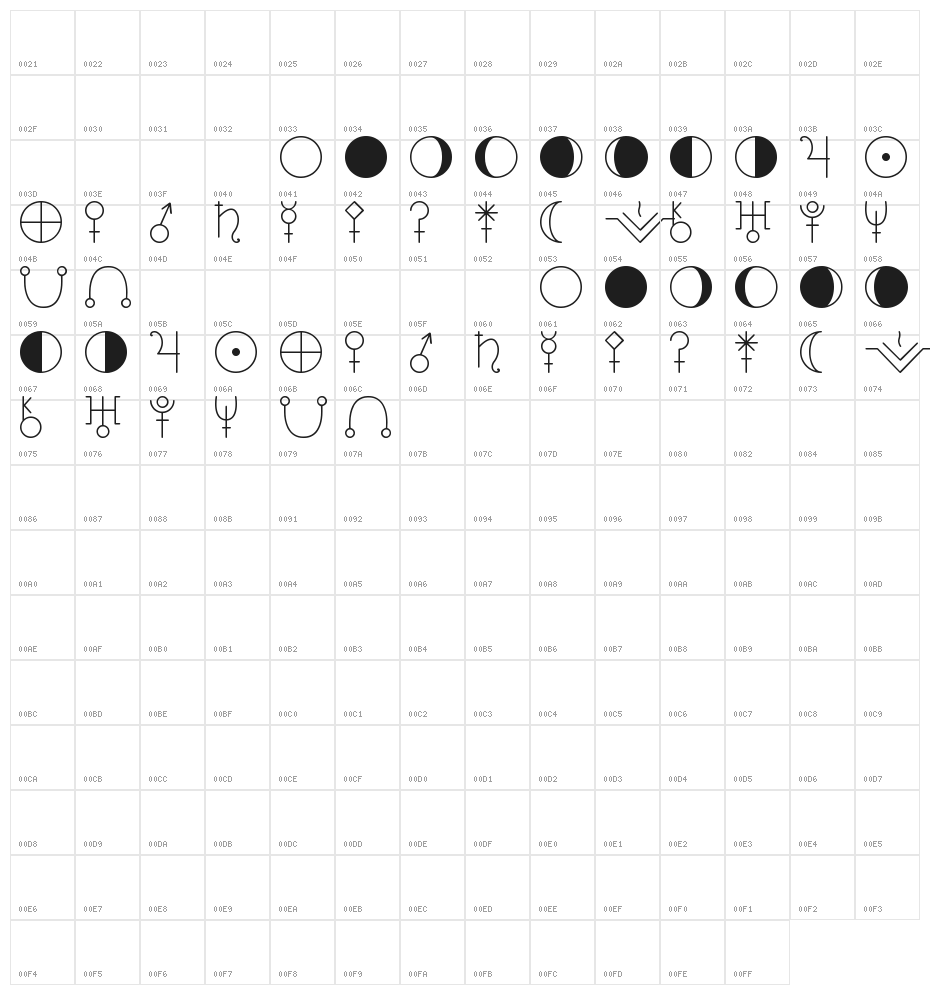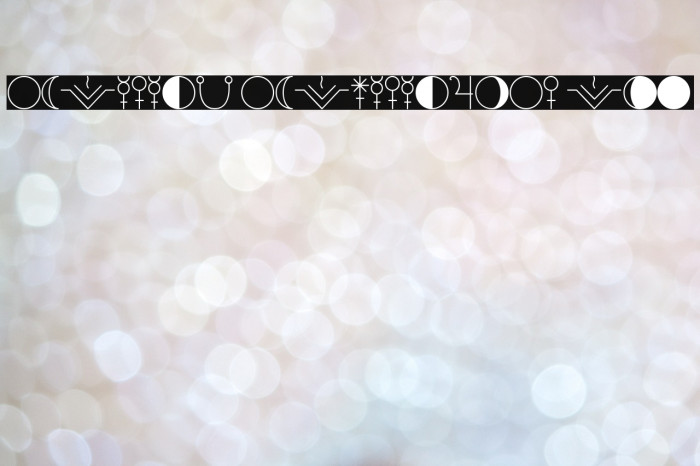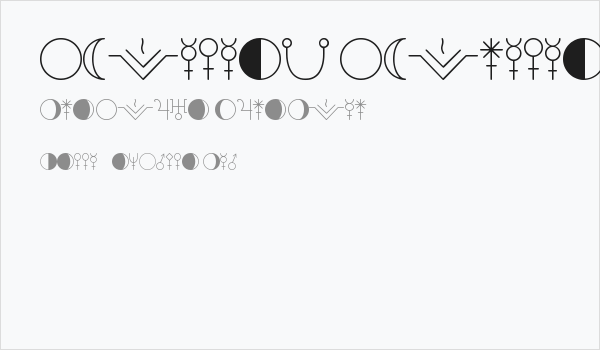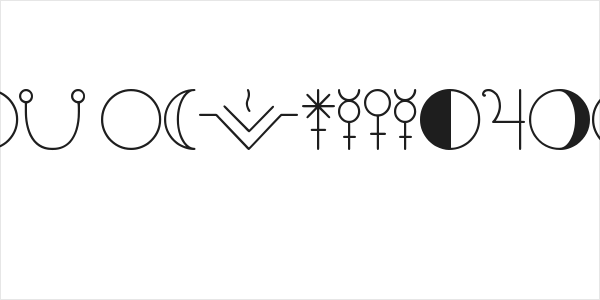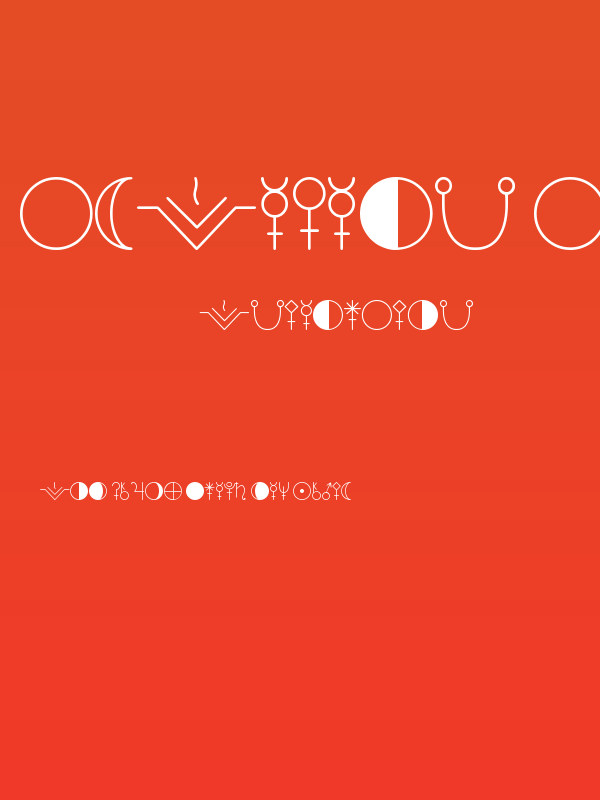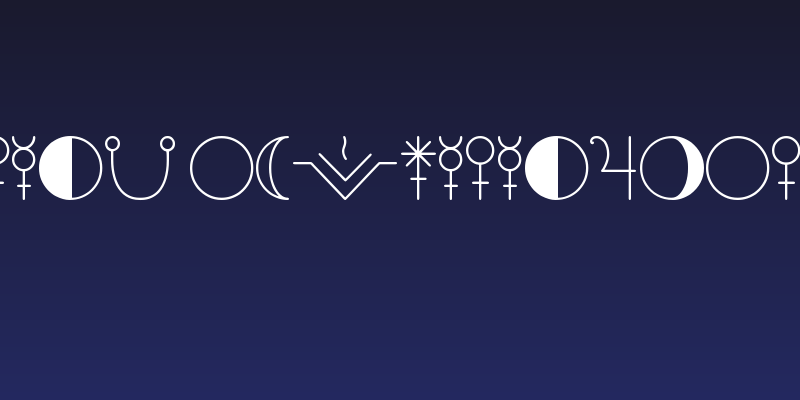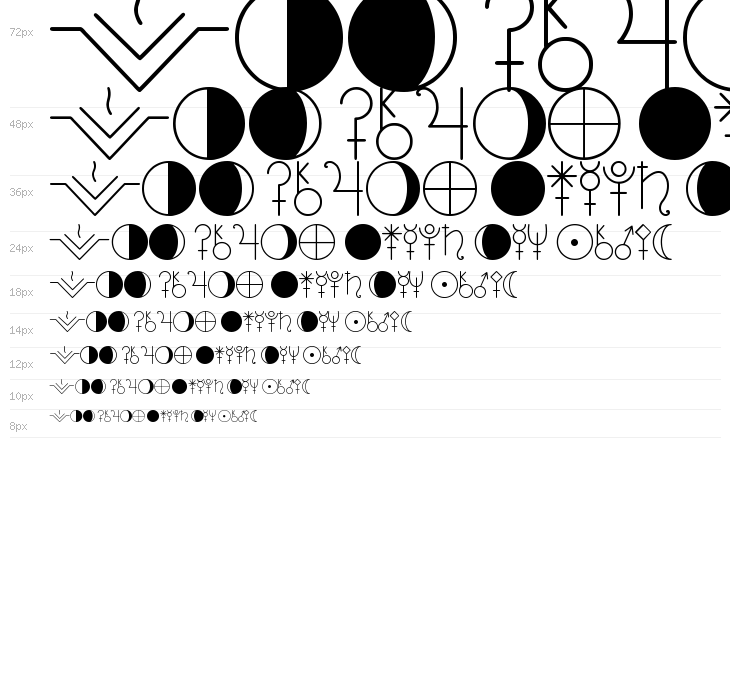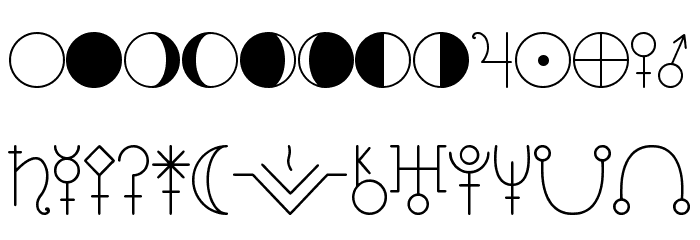
ASTOLOGY ASTROLOGICAL TFB Font
| समग्र शैली | Mystical, Cosmic, Geometric |
| उपयोग का मामला | Logos, Posters, Themed Designs |
| सुझाए गए प्रोजेक्ट | Ideal for astrology-themed designs, horoscopes, cosmic event posters, and mystical branding. |